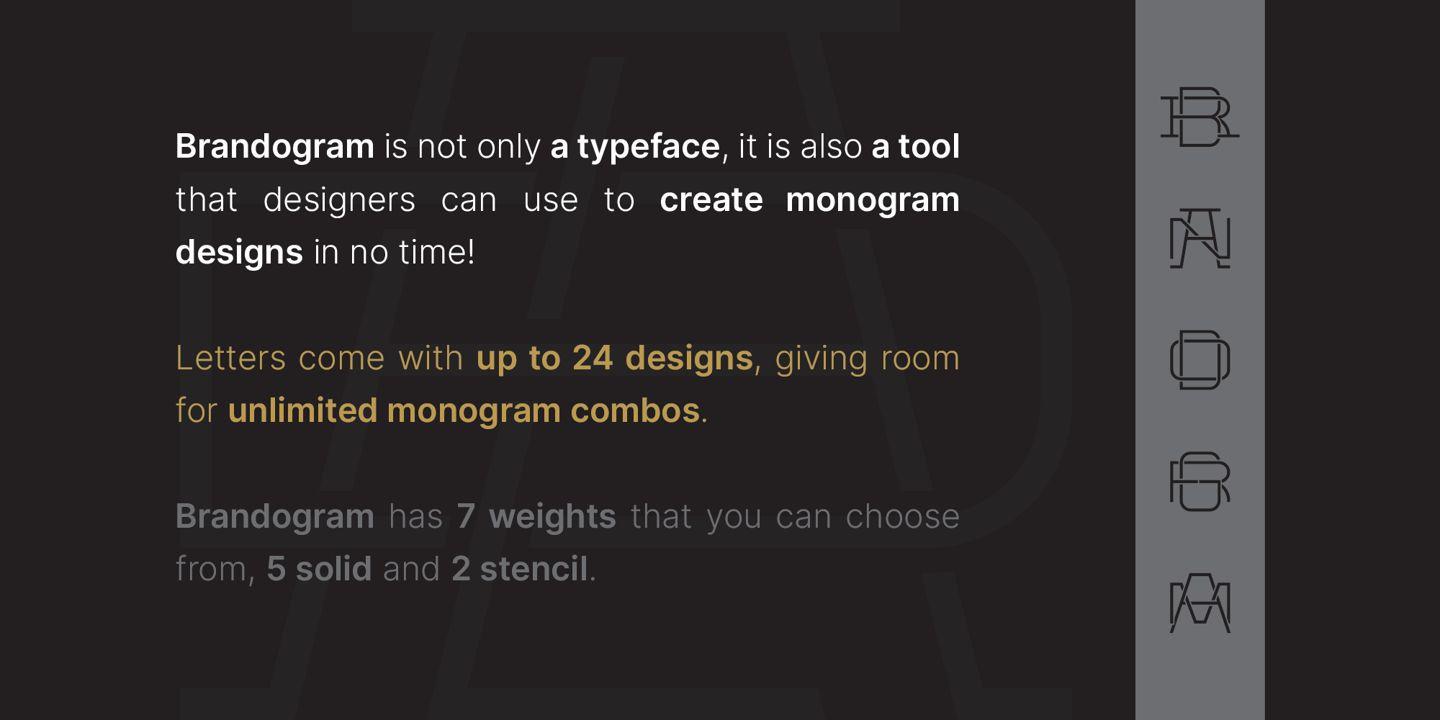
Brandogram Font Family
Après des mois de tests et de développement, nous avons réussi à mettre au point le Brandogram Typeface, un outil ultime pour la conception de monogrammes. Avec l’aide de cette police, vous pouvez facilement créer un monogramme en moins d’une minute. Grâce à la façon dont nous avons créé et optimisé Brandogram, les lettres majuscules s’emboîtent sans effort avec les petites majuscules activées par les lettres minuscules.
En utilisant la police Brandogram, vous pouvez créer des combinaisons de monogrammes illimitées avec 2, 3 ou même 4 lettres dans certains cas. Et tout cela est possible grâce à des fonctionnalités telles que :
– Plusieurs largeurs de lettres, de condensées à larges ;
– Modèles de lettres sans empattement et avec empattement ;
– Jusqu’à 24 designs différents par lettre ;
– Toutes les variantes de lettres sont disponibles en remplacement afin que vous puissiez facilement choisir votre préférée ;
– Des accents sont disponibles pour chaque lettre alternative ;
– Les lettres activées majuscules et minuscules sont construites pour s’aligner parfaitement au centre et au milieu ;
– Il y a 5 poids solides prêts à l’emploi ;
– Il existe 2 autres poids de pochoir qui peuvent apporter une nouvelle touche à vos créations.
On pense que chacun de ces poids exprime différents niveaux de lourdeur. Plus le poids de la police est épais, moins il restera d’espace blanc entre les lettres lorsqu’elles seront combinées, donc votre dessin deviendra plus lourd. Le rôle des poids du pochoir est de créer de la profondeur dans les dessins de monogrammes. Avec ceux-ci, vous pouvez facilement supprimer les formes supplémentaires des lettres qui se chevauchent, créer des passages entre les lettres et donner une impression d’emboîtement.
Cette police combinée à votre créativité ne peut avoir aucune limite !